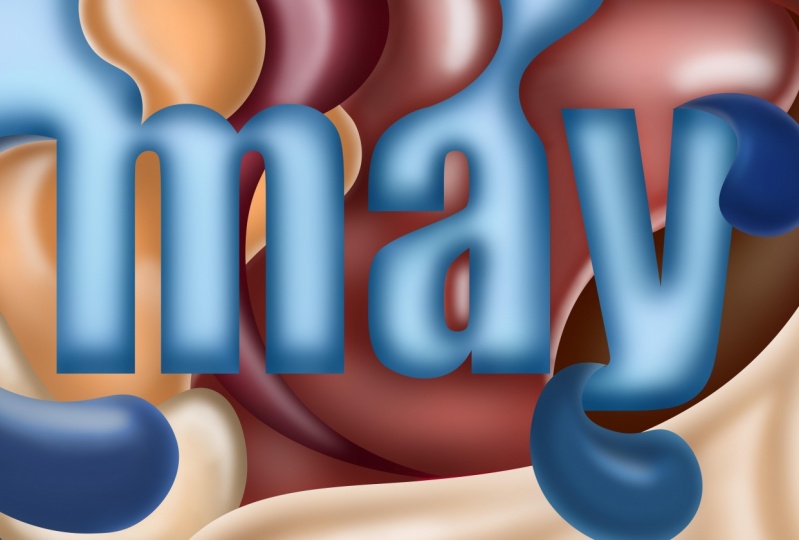
Tipografía creativa y arte abstracto del concepto de remolino
En este curso, enseñaré cómo puedes usar las formas básicas en Adobe Illustrator y Photoshop para crear hermosas obras de arte abstractas que pueden usarse para el diseño de embalajes, pósters o proyectos divertidos personales.
Te guiaré a través de todo el proceso de crear las formas en el ilustrador y importarlas en Photoshop STEP-BY-STEP. Mostraré cómo distorsionar las formas alrededor del texto con la herramienta de pen en el ilustrador, o crear todo directamente en Photoshop sin usar Illustrator. También te mostraré cómo usar máscaras de recorte y sombreado para que las formas planas aparezcan en 3D y tengan un efecto brillante para ellas.
1. Introducción: hola y bienvenidos a esta clase sobre la creación de arte abstracto tres D divertido en Adobe Illustrator y Photoshopped. Recuerdo cuando aprendí por primera vez a crear arte como este, y realmente trajo mi diseño gráfico a un nuevo nivel, y la gente estaba mucho más impresionada con este tipo de ilustraciones que crearía para diseño de carteles o producto diferente embalajes. En este curso, todos vayan contigo, paso a paso para esbozar tu obra de arte y traerla en ella será ilustradora y fototienda. Te mostraré cómo crear formas, usando la herramienta lápiz y otras herramientas e ilustrador para obtener los conceptos perfectos que quieres retratar. Entonces te mostraré cómo llevar tu obra de arte a la fototienda y luego, usando técnicas de pintura digital y cepillado, te mostraré cómo agregar profundidad y sombras y reflejos a tu trabajo para realmente traerle una profundidad de tres D a ella. Me encanta crear este tipo de arte, y puedes usarlo en concepto de packaging de producto son arte de póster divertido o una variedad de cosas diferentes. Me emociona ir junto con ustedes en esta clase y ver algunos de sus proyectos tan pesados y rollar botón y empecemos 2. Crear los bocetos de concepto: así que para empezar, me gusta esbozar una idea básica general de lo que voy a estar haciendo. Sólo que tengo un buen punto de partida cuando me meto en Adobe Illustrator y Photoshopped. Esto no es alguien que tenga que hacer. Y así podrías saltarte este video si quieres, pero esto va a ser una idea general de qué? Voy a empezar. Entonces voy a bosquejar Solo el general son nuestra zona de juntas, y voy a tener este aspecto como un diseño de empaques para, como, helado o leche o algo así. Entonces voy a tener, como, como, un gran movimiento en ello, Digamos que va a ser como un anuncio o algo así. Entonces eso es en, uh um y ha sido esto fuera un poco más. Y así tengo mi texto y voy a tratar de dibujar algunos grandes ya sabes, helado o remolino buscando formas alrededor de esto. Toma este diseño de fondo. Entonces vamos a tener la parte superior de la M. Es stand en esta zona. Y como dije, solo estoy tratando de tener una idea general de algunas formas diferentes para que esto se vea un poco más orgánico, y quiero integrar el texto en las formas. Por lo que parece más que forma parte de la ilustración y de esta cantidad aquí. Y no tengas miedo de agregar algunas formas realmente grandes. Alguna mente, incluso encubrir un poco el texto. Tan solo quería lucir realmente fluyendo y tener una buena sensación al respecto. Algunos invitados dan un poco esta siguiente parte para que veas lo que estoy haciendo ahora. Ya que querían tener más de una sensación lechosa y fluida, voy a añadir algún tipo de formas de gotitas grandes. T tener un poco más de diversión con un como este. - Entonces ahora que estoy hasta este punto, se puede ver que hay todas estas formas diferentes y todas parecen que están fluyendo juntas. Y todas estas grandes gotitas que puedes ver que tengo aquí hubiera hecho es que he pasado por algunos de los bordes, derecho tengo aquí NF acabo de dibujar y saliendo de esos bordes así como este, por ejemplo Puedes ver este borde lo hago por aquí y luego acabo de agregar que entrando así parece que fluye hacia las formas y Así que eso es algo que puedes tener en cuenta cuando estás dibujando algunos de tus diferentes remolinos o formas. aire que sale de él es que puedes tener esos fluyendo a diferentes rincones y hendidura para que se vea un poco más integrado en tu diseño. Y así no es perfecto. Pero al menos ahora tengo un buen punto de partida y conozco la dirección que quiero ir. Una vez que puse esto en Photoshopped, un ilustrador. Entonces ahora lo que voy a hacer es agarrar mi teléfono o puedes conseguir un escáner, y sólo voy a tomar una foto de esto de verdad rápidamente para referencia, y luego voy a tirarlo un ilustrador. Empezaremos en el siguiente video. 3. Añadir formas y conceptos en Illustrator: Por lo que hay dos formas de crear esta obra de arte. Ambos están consiguiendo este show fotográfico. Pero una manera es ilustradora, y la otra forma es simplemente quedarse en la tienda de fotos con todo y hay algunas ventajas para cada uno y las desventajas enseñan. Y así te voy a mostrar el en el sectorial en ambos sentidos para que puedas decidir qué va a funcionar mejor para tu proyecto. Entonces lo que voy a hacer es iniciar ilustrador para esto y agarrar el boceto que hice para el concepto. Entonces voy a copiar eso y luego volverlo a poner. Illustrator a usar es mi referencia. Entonces solo voy a escalarlo un poco y como ha terminado en el video de periodos, esto solo va a ser una idea áspera en Así que tú Lo que puedes hacer es usar la herramienta de bolígrafo o como quieras , y en realidad ir a través y mano, dibujar todo tu tipo, o puedes usar solo algún fondo. Y en realidad tengo un fondo que basé este tipo alrededor, um, um, digamos otra vez suave. Y así lo voy a escribir para que ya lo tenga aquí mismo. Y así centraré esto en nuestra pizarra donde me gusta, Eso se ve bien. Y luego tocaré turno, y luego control o mando. Ah, y eso va a crear estos contornos para que pueda trabajar más fácilmente con nosotros. Ahora, una de las otras cosas que va a ser importante es tener una buena paleta de colores. Y entonces lo que me gusta hacer es ir a, uh, color adobe. Entonces color adobe dot com. Y, uh, tienen realmente buen recolector de color. Este es un parecido al de ilustrador para esto solo voy a ir a explorar y solo voy a encontrar un esquema de color que ya me gusta. Y así, para mi tema, estoy pensando que voy a ir por una especie de look de chocolate. Y así vamos a ver qué surge cuando tipeo en chocolate. Y así estos aires unos colores de aspecto divertido, me gusta tener un poco de azul ahí dentro. Entonces solo voy a guardar esto, y luego va a ir directo a mi biblioteca. Y así voy a crear nueva biblioteca. Llámalo nuevo. Entonces una vez que tengamos todo esto ahora voy a ahorrar, y ahí está Así que voy a volver a Adobe Illustrator y quiero sacar mi panel de biblioteca, así que ve a ventana y luego bibliotecas y ahí va a sacar todas mis bibliotecas, así que iré a biblioteca y aquí está mi biblioteca mu. Y vi personas que han tenido problemas con nosotros en el pasado que no se hunde con sus bibliotecas. Y así solo quieres asegurarte de que tus bibliotecas estén actualizadas. Es posible que tenga Teoh haga clic en uno de estos iconos y asegúrese de que tiene la actualización puesta a hundirse, y luego aquí está su paleta de colores. Y así voy a, derecha, Haga clic en eso y diga, agregue dos muestras. Y ahora aquí tengo todos estos colores añadidos a mi panel de muestras. Y así para esto, quiero que el texto principal del estado de ánimo sea una especie de blanco, y así lo voy a agregar a ese color, y puede ser un poco difícil de ver, Así que por eso solo lo hará azul por ahora. Y luego voy a empezar a dibujar algunas de las formas del concepto Sketch lo hizo. Y así aquí mismo, voy a añadir esta M estirándose en todas estas diferentes formas estaban aquí tan hippie para mi herramienta de bolígrafo, y voy a hacer clic arriba en la parte superior de ellos. Y quieres asegurarte de que el punto de anclaje esté chasqueando aquí mismo. Y así me voy a asegurar que eso encaje al punto de anclaje y uso ah, control o espacio de comando. Yo los sostengo abajo para el matorral, tú zoom e ilustrado porque lo hace un poco más fácil. Y pincharé aquí arriba y luego mantendré pulsada opción o Alter y puedo mover punto de anclaje alrededor y cambiar para limitarlo. Y luego pincharé por aquí abajo, ya sabes el fondo y luego lo traeré por ahí. Y si se pone difícil de ver porque el ilustrador rellena la forma automáticamente golpeará Mayús X, y luego simplemente lo cambiará a delinear en eso y oh, haz clic arriba por aquí y el hombre de nuevo a la M. Asegúrate de que broches de presión y conectados ahí mismo. Eso me gusta ahí mismo. Entonces voy a golpear opción o todo para conducir el punto de hundimiento otra vez y luego cerrar el camino y luego volveré a golpear el turno X para llenar esa forma de nuevo dentro. Y ahora aquí mismo, no conecta todo el camino. Suela. Usa mi herramienta de selección de drogas golpeando un y luego daré clic en este camino aquí mismo. Y solo arrastraré eso hacia abajo y luego pincharé en este punto de anclaje y lo arrastraré un poco más para que quede un poco más fluida de eso. Y ahora, para asegurarme de que esto no es demasiado torpe aquí mismo, agarraré ese punto de anclaje y solo arrastraré esto un poco hacia arriba. Y en realidad me gusta eso porque agrega un poco más de piso ahí mismo. Y tengo esta gota aquí mismo que voy a dibujar, así que haré lo mismo. El P para el lápiz. Empezaré aquí mismo y me voy a arrastrar y no me importa superponer formas. Entonces aquí y allá en un barco X. Asegúrate de que pueda ver lo que estoy haciendo y arrastra por aquí. Y luego cuando quiera cerrar el camino para asegurarme de que se quede de esta forma todo hit opción o todo primero y luego voy a hacer clic y mantener presionado y luego puedo arrastrar el punto de anclaje por donde quiera. Y así lo voy a cerrar ahí mismo. Y luego utilizo una herramienta de selección directa y solo ajusto un poco las cosas. Asegúrate de que sea agradable y suave, y eso se ve bastante bien. Y luego, uh, golpeó turno X otra vez. Y solo voy a hacer de esto un color diferente para que puedas verlo. Y voy a sólo unas cuantas cosas este año en un poco más. Entonces eso se ve realmente bien. Y voy a pasar por esto y hacer lo mismo con algunas de estas otras formas. Ve a Theo, conduce alrededor, opción, luego haz clic y arrastra. Y luego, ya sabes, conecta eso aquí mismo para asegurarte de que parezca que es parte de la O. Y él es mi herramienta de selección directa y ajustar la mitad sólo un poquito. Y ahora se puede ver aquí mismo. Algunas de estas ha quizá no estén totalmente conectadas, y así que solo quiero pasar y asegurarme de que esos aire todo se rompió a las formas. Porque cuando exporto esto, traiga una tienda de fotos. No queremos ningún problema con las formas que no se conecten. Y una cosa que va a ayudar con muchos de ustedes probablemente sea llenar primero el fondo , porque esa podría ser una de las cosas más difíciles de averiguar una vez que haya llegado a cierto punto. Y así lo que puedes hacer es solo que tu herramienta de lápiz y luego simplemente haz clic y luego solo rellena algunas formas de fondo grandes, y eso es un poco demasiado lejos. Entonces voy a No vas a bajar un poquito. Ponla aquí y ahora quiero algo Eso es tabaco hit shift command y soporte izquierdo o control de turno y Soporte izquierdo. Y luego voy a cambiar el color y puedes ver que está en el fondo. Y así voy a llenar unas cuantas de estas formas en el fondo sólo para que todo esté cubierto y no tenga que preocuparme por ello tanto más tarde y equipo aquí y ella está mando dejó corchetes y de vuelta a la espalda, y yo te tire hacia arriba en mi panel de color y puedes tener esto expandir y colapsar. Pero hasta que veas estos controles y me gusta usar el modo de brillo de saturación de matiz para que pueda cambiar, las cosas serán más fáciles. Eso es lo que prefiero. Y así ahora nos estamos llenando mucho más. Y voy a golpear la M para mi herramienta de forma y simplemente arrastrar una caja justo aquí para poder llenar el resto de esto con bastante facilidad. Y entonces los hombres deberían dejar corchetes y eso a la espalda, y voy a usar otro tono de marrón. A lo mejor un poco más de saturación ahí dentro. Y ahora que tengo todo el asunto, Phil, entonces realmente puedo hacer el movimiento y algunas cosas otras formas blancas como, originalmente quería. Y puedes empezar a cantar como se va a ver. Y así ahora esto realmente está empezando a tomar alguna forma. Voy a añadir algunos remolinos más aquí mismo. Bueno, gotita de leche saliendo de su retención en opción para sacar ese punto de anclaje, utilizo mi herramienta de selección directa. Digamos que esto está cubriendo eso un poco demasiado algunos y arrástrelo por aquí anime y entrar, acercar un poco más y asegurarnos de que eso parece que se está conectando derecho a eso . Ah, porque lo que vamos a hacer es agregar algunas sombras más tarde, así que parece que está frente a la y está saliendo de ella. Entonces conduces eso y un poco más ahí mismo. Vamos a hacer esto un poco diferentes tonos de color sólo para que pueda ver dónde está . Y no estoy demasiado preocupado por ello porque voy a meterme con todos estos colores después de todos modos . Y así ahora tengo esta gran forma saliendo de aquí que quiero tapar algo de eso Oh , con Teoh. Añade algún tipo de efecto drama divertido tan bien, más rápido fuera de aquí y arrastra eso hacia abajo y hazlo subir justo ahí. Opción, conducir el punto de anclaje por aquí. Genial ahí y luego agrega una línea grande justo aquí. Y no estoy demasiado preocupado por ser súper preciso porque, como dije, sólo voy a seguir, mover las cosas de todos modos. Buen sinker jugando y todo eso. Y así que esa es una gran corriente de leche que viene ahí mismo. Y una cosa que vas a querer mirar es un contraste, porque si tengo demasiado de este blanco, entonces va a ser más difícil ver ese texto. Y así tengo un poco de azul en mi paleta de colores, así que tal vez quiero hacer esta forma azul, y luego puedo agregar algunos. Por qué las formas que salen de eso aquí mismo. Ahora que tengo esta porquería hecha, voy a ajustar un poco y que cuando pueda hacer blanco, porque no va a ser tanto que va a dominar el texto en el medio. Y así ahora el resto de esto, voy a hablar un poco más rápido. Vamos a añadir un poco alrededor del cabello y otro truco que me gusta usar si estoy creando algunas formas al igual que esta forma que tengo aquí y lo quiero detrás de ciertas formas. Pero frente a otros para controlar que solo puedo golpear control o comando X, Y entonces puedo buscar las formas que la quiero delante y detrás. Entonces, por ejemplo, puedo ver todas estas formas aquí mismo están frente a ese gran bloque marrón, y quiero que esa forma que acabo de hacer para estar entre esas y los soldados golpearon ese bloque marrón . Y luego si vas dedo del pie editar, puedes haber dado un paso al frente. Y ahora va a ritmo esa forma frente al bloque que había seleccionado, pero detrás de todo lo demás que está delante de ese bloque y cambiaré ese Teoh diferente color azul y ajustaré un poco la forma. Y ahora algunas de estas otras formas de aquí voy a entrar, y eso termina ahí mismo y lo mismo, Control X y yo queremos que estemos frente a todas estas formas de Brennan, y así esto está frente a eso. Y así le pegaron al control F, y ahora está detrás de ese azul. Pero ahora, como parece que quiere pasar todo el camino por esto, sólo voy a extenderlo por aquí con otra nave. Entonces esa es una de las ventajas de iniciar esto es un ilustrador. Es realmente fácil trabajar con, y tengo muchas herramientas que pueden controlar lo que estoy haciendo. Entonces oye, controla X y luego quiero que al mismo nivel es esto? Entonces voy a dar clic en esto y luego golpear el control F, y ahora se trata justo ahí, aunque tengo esta otra forma marrón que está delante de eso porque se puede ver donde está apareciendo ahí mismo. Entonces solo voy a agarrar esa forma y golpear el control y luego me fui Bracket, y tiene que mandar eso de vuelta. Sólo un objeto. Y así me estoy acercando realmente. Ahora puedo ver esto. Ahí está esta gran mancha que se está poniendo, ah como en el camino con algunas de estas tangentes. Entonces voy a cambiar el color en estos solo un poco y hacer un poco más brillante, y voy a golpear mi total de rotación son para la herramienta de rotación, y voy a dar clic en la base de eso Y sólo voy a girar un poco justo así eso no está causando tangentes divertidas en estas áreas, y sigue haciéndolo sólo un poquito. Entonces lo voy a mover allá arriba ahora se ve un poco mejor, y quiero unas gotas aquí mismo. Y así solo voy a golpear el control C y luego cambiar el control o comando V, y voy a dar clic en eso y Hit pidió mi herramienta de escala click en la parte inferior de aquí y sólo voy a bajar eso un poco. Y no voy a sostener turno porque no me importa tanto ser proporcional porque quiero lucir un poco diferente a eso. Y así me gusta eso y hago vamos a hacer este chocolate y así sucesivamente. Y creo que esto se está acercando realmente. Sólo voy a tener una forma más aquí arriba detrás de ahí. ¿ Es ese un color diferente del azul? Y aunque es bueno y voy a golpear el control X y solo quiero colocarlo justo detrás de eso , lo vemos para hacer eso, puedo tener objeto y luego o editar y luego pegar en la espalda. Y eso sólo va a pagar Siéntate detrás del objeto que tengo. Um, un problema aquí mismo es que tengo esa forma al frente y así no hay nada que necesito detrás de esto están frente a esto. Y así sólo voy a tener control de turno, soporte derecho, y eso lo va a mandar al frente. Ahora da click en esto y quiero que esto solo sea un tono diferente de azul ahí mismo. Entonces haz clic ahí y voy a ir a mi barra de saturación de matiz. Y luego estaba desnatando sin un poquito y hagámoslo un poco más oscuro, y quiero que esto tenga una transición mucho más fluida con esta otra forma. Algo es mi herramienta de selección directa. Y sólo voy a arrastrar esto a la derecha para que esté conectado con ese, y luego voy a tirar hacia arriba. Y así ahora tengo esta pequeña tangente en el camino ahí mismo, así que sólo voy a subirla un poquito. Entonces no está causando ningún problema por ahí. Y así creo que esto se ve bien. Y ahora te enseñaré cómo prepararlo. Teoh, trae a Photoshopped. 4. Preparación de obras de arte para Photoshop: Voy a eliminar esta referencia ahí tengo, y voy a agarrar todas estas capas y asegurarme de que puedas ver qué está pasando. Voy a dar click en mi posterior en mi panel de capas y voy a ir a este pequeño menú para el panel y voy a dar click en liberar dos capas como secuencia. Y ahora lo que va a hacer es separar todas estas capas en su propia capa individual. Y así voy a dar clic en todos estos y todos arrastrar aquellos fuera de esa capa principal y luego voy a clic en esa capa original uno. Voy a golpear delete porque no hay nada en él y sólo voy a asegurarme de que haya algo en todas estas capas y todo se vea bien. Bajaré a archivar y luego a exportar como, y voy a ir al archivo que quiero, y lo voy a guardar como tienda más. Nuevo. Son mundos. Ah, quiero asegurarme de que estoy usando los nuestros tableros porque eso lo va a recortar a la zona que tengo en mi están aburridos. Tengo este cultivo, así que tengo alguna forma saliendo. Pero si sí tienes formas saliendo. Vas a querer asegurarte de tener tablero de arte seleccionado cultivo de cereal cualquier imagen extra fuera , y luego tendré exportación. Y quiero asegurarme de que sea un RGB y tendrá, Ah, alta resolución. Quieres tenerlo configurado para escribir capas y estás máximo sin marcar en una habilidad de edición y luego golpear. Está bien. Y ahora en el siguiente video, te mostraré cómo abrirla y Photoshopped. 5. Importación en Photoshop: De acuerdo, así que ahora ya estás listo para abrir ese archivo Y Photoshopped, Vamos a abrir la cabeza y dar click en la primera falta de disparo que creamos y que había abierto. Y ahora tenemos la misma obra que exportamos de Adobe Illustrator. Si lo hiciste bien, deberías tener todas estas capas separadas y el panel de capas como sus propias capas individuales . Y la canción de grupo de esta tiene el comando de turno G y en grupo eso y de hecho, esa es mi capa de texto principal. Entonces sólo voy a nombrar eso sin texto. Y ahora lo que me gusta tener es mi auto select and show transform controla un cheque para que pueda seleccionar fácilmente diferentes capas. Y puedo ver los controles de transformación en esos. Y me gusta que después seleccione porque eso significa que va a seleccionar cada capa individualmente. Y así ahora que estoy en este punto, quiero seleccionar este texto de ánimo y estas otras dos capas y veamos dónde están en su en diferentes áreas. Y así voy a arrastrar esta capa que está clara en la parte superior, y la voy a arrastrar hacia abajo a esas otras capas, así que la voy a arrastrar hasta y la voy a arrastrar hacia abajo a esas otras capas, aquí, pero ahora puedes ver y moverte hacia arriba debajo de esa otra capa azul. Y así lo que puedo hacer es hacer clic en esta capa y golpear control o comando, y luego todos seleccionar esa capa, esta transparencia trans Lexa de esa capa. Y luego voy a dar click en esta forma azul que quiero lucir como está detrás de eso y luego encontraré donde está la forma azul, y luego solo voy a dar clic en esta herramienta de máscara pega toda nuestra opción, y luego voy a dar click en eso. Y eso va a eliminar todo lo que he seleccionado de eso más adelante. Pero lo bonito de esto es que si sostengo turno y hago clic en la máscara, sigue ahí. Por lo que todavía puedo usar eso si necesito. Y ahora que todas estas capas se están tocando aquí mismo, puedo golpear el control o el comando E, y eso las va a fusionar todas juntas porque quiero que estas todas estén conectadas para que cuando la esté cepillando, sea va a ser mucho más fácil, y eso se ve bien para todo lo demás. Una cosa que quiero asegurarme de que también hago es ir a mi imagen y luego cambiar el modo a 16 bit. Y eso lo va a hacer para que mientras te estás cepillando en algunos de los diferentes sombreados y colores en esto, um, no va a haber bandas. En ocasiones notarás si estás metido un poco cuando estás usando la herramienta de pincel o pintando. Verás esto, uh, uh, genial y banding que va a causar líneas y distorsiones en tu obra de arte. Por lo que tenerlo en 16 bit es bueno para mientras estás trabajando en él y luego puedes cambiarlo nuevo a un poco más tarde. Y así nos vemos bien aquí mismo. Sólo recuerdo que me quedan estas dos formas que me refiero a moverme un poquito por esos tendones ahí mismo sobre el él. Y luego golpearé Control E y me aseguraré de que esos aire se fusionaron juntos. Y eso es todo lo que necesitas para que esto se prepare para empezar a pintar. Y así en el siguiente video, te voy a mostrar cómo empezar a sumar algunas de las diferentes sombras y reflejos para realmente hacer de este nuestro trabajo de un destaque 6. Añadir sombreado y profundidad a la ilustración: De acuerdo, así que ahora por la parte divertida, voy a Teoh, encuentra algunas formas que quiero empezar a agregar. Ah, algo de profundidad al primero. A mí me gusta empezar con un fondo y trabajar mi camino arriba, así que voy a empezar el fondo. Añadiré una nueva capa justo aquí encima de ella y luego mantenga la opción o todo, y luego haga clic para que se vaya a crear una máscara de recorte en la parte superior de esa forma inferior. Y entonces tendré esta forma aquí mismo, y haré clic en el modo de mezcla y pasaré de lo normal a multiplicarse. Y esto solo organiza mis capas para que pueda tener mucho más control sobre lo que está pasando . Y así ahora tendré carne de res con herramienta de pincel aquí y todo bien, click y luego escalarla y asegurarme de que la dureza sea un cero. Y lo que también me gusta hacer en Ah, oye, mira, puedes tener opción y luego hacer click derecho y arrastrar de ida y vuelta y de lado va a cambiar el tamaño y arriba y abajo. Esto puede cambiar la dureza, y se puede ver aquí mismo hay un pequeño adelanto rojo de cómo se va a ver si tuviera cero, eso va a cambiar mi capacidad. Uno es 10 cinco o seis. A 60% 0 va a ser 100%. Y ahora puedes ver ese adelanto un poco mejor. Y en nuestro Mac, el atajo es control, opción e izquierda, haga clic y arrastre de ida y vuelta. Entonces ahora que tengo mi color seleccionado, estoy en un color oscuro y voy a empezar en, como, 30%. Y voy a empezar a cepillarme donde quiero algunas sombras, y eso se ve un poco demasiado oscuro ahora mismo. Así que voy a golpear controles, oído Comando Z, y voy a bajar al 10% y, uh, acercar un poco y luego sólo añadir eso aquí un poco, justo donde parece que hay una sombra detrás de eso forma, y voy a añadir un poco detrás de Mary, y voy a añadir algunos por aquí y empezar a añadir sombras sólo un poco donde va a traer un poco de muerte, y eso está un poco demasiado oscuro ahora. Y puedo hacer esto un poco más grande y de repente poner en algún chef está justo ahí. Y así eso es lo que puede conseguir para los hombres en. Y ahora voy a añadir otra capa encima de eso y luego tenía opciones son todas y luego hacer clic en crear, no equipar máscara y luego cambiar ese modo de mezcla a la pantalla enter. Y ahora volveré a usar mi herramienta de pincel. Y luego le pegaré a X para asegurarme de que esté sobre blanco. Y luego entraré y añadiré algunos reflejos blancos, y eso se ve un poco demasiado justo ahí. Y así le pegaré a Control Z. Y luego mandaré mi pasividad abajo para decir como, tres personas. Y eso ya se ve un poco mejor aquí. Y agreguemos algunos aspectos destacados por aquí. Entonces estamos ahí dentro y tiene unos bordes más afilados, y ahora eso ya está sin duda se ve bastante bien aquí mismo. Y lo que puedo hacer para suavizar todo es que puedo seleccionar mi capa aquí mismo, que un filtro y luego desenfocar, y luego simplemente Goshen desenfocar. Y luego si desenfoco eso, lo va a suavizar aún más. Y en este momento solo estoy tratando de bajar algunos colores base como punto de partida para agregar algo de profundidad a esto, así que voy a dar clic en las sombras. Y luego, en lugar de ir a Teoh Goshen, difumina cada vez. Solo puedo usar mi filtro más reciente con un atajo corto. A te da justo aquí, así que eso es control a la izquierda. Entonces voy a golpear el control F, y automáticamente va a desenfocar esa capa. Y así ahora que estoy listo para empezar en mi siguiente capa, solo haré clic en esa capa. Y lo que he hecho es crear una acción, así que no tengo a Teoh seguir creando nuevas capas y enmascarándolas a esa capa inferior. Puedo entrar en mi panel de acciones, y si vas a la descripción del curso, tengo un enlace a esta acción donde puedes descargarlo. Y si quieres carga de dedo, la acción y yo tengo que ir a es el menú arriba en el panel y tenía acciones de carga y luego seleccionar el archivo. Y una vez que estés listo, solo tienes que hacer clic en la capa que quieras y luego hacer clic en la acción en ella jugar, y luego crea automáticamente estas dos capas y como el modo de mezcla correcto. Y así ahora solo puedo hacer clic en la capa inferior y usar mi herramienta de pincel y asegurarme de que esté en negro y empezar a cepillarme en algunas sombras. Voy a hacer este 10%. Iba a cepillarlos y un poco mejor. Y como algo de sombra aquí abajo, un poco más de escritor ahí dentro. Ahora todo lo que estoy haciendo es hacer la ilusión de que hay profundidad con estas capas. Y así tengo esta capas marrones de mi capa inferior. Esta está ligeramente por encima de eso, y así estas capas se airean encima de eso. Una vez solo estoy agregando algunas sombras más y reflejos Teoh, donde estas capas o creando sombras en estas y se ve bien. Voy a golpear control o comando f explorar eso un poco. Y este tu desenfoque más reciente no fue suficiente. Entonces solo puedo volver a entrar y desenfocarlo a algo que quiero escoger manualmente, y eso fue un poco mejor ahí mismo. Y ahora entraré en la capa de resaltado y añadiré algunos reflejos. Ve al 3% si hay esa experiencia de una milla aquí y hagamos esto un poco más brillante. Entonces tengo un punto culminante decente ahí mismo, y queremos un buen resaltado y hagamos que parezca que este chocolate de aquí está viniendo fuera de eso está viniendo a través de eso. Ah, así que para hacer eso, solo le agregas un poco de reflexión encima. Y ahora solo difuminemos esta capa aquí mismo. Ahora suaviza un poco esos reflejos. Y ahora esos se ven realmente bien ahí y en realidad se pusieron un poco más detallado puedo entrar aquí y luego sólo voy a añadir otra capa nueva, opción tirar hacia abajo o todo. Asegúrate de que recorté eso hasta ahí. Y luego voy a usar mi lápiz herramienta hit p con lápiz aquí. Y ahora puedo empezar a ser un poco más precisa sobre dónde quiero añadir algunas de estas reflexiones. Entonces voy a dar clic aquí, y luego voy a añadir una reflexión justo alrededor de esta zona. Y luego este trabajo similar al ilustrador puedo mantener presionada toda la opción y luego arrastró el punto de hundimiento alrededor y luego dr por aquí así, y luego mantener presionadas todas sus opciones primero. Y luego puedo ajustarme donde quieras ese último punto pensador, y eso se ve bastante bien. Y así da click en esa capa que quiero usar como línea de reflexión justo ahí y luego todo hit control o comando. Y luego golpearé la máscara de recorte y eso va a crear una máscara para la capa vectorial desde ese camino hacia esta capa. Y eso es realmente bonito, porque entonces puedo controlar la máscara más tarde. Y este es un uso técnico, uh, para crear este arduo trabajo desde cero si no quería usar ilustrado. Y así tengo eso ahí mismo. Voy a dar clic en la capa y luego golpear mi herramienta de pecho y luego asegurarme de que estoy en blanco y luego todo de solo cepillarnos un poco de reflexión ahí mismo. Y tal vez eso es un poco demasiado, uh, arrastrar la capacidad. Y luego, si tengo esto seleccionado, si tengo mi panel de propiedades arriba, puedes ir a ventana y propiedades. Eso te va a dejar mientras esto esté seleccionado, cambiar el emplumado y los algunos de los ajustes de la máscara, y así si quiero una pluma que enmascarar un poco, entonces empieza a un poco más de profundidad. Y así lo voy a hacer un par de veces más con la misma capa en zonas, creo que habría un reflejo. Entonces esto me estoy imaginando un reflejo de la O donde esa línea recorre ahí mismo. Y así va a ser este pequeño reflejo falso ahí mismo. Y podría hacerlo de nuevo aquí mismo en otra capa. Y solo puedes seguir haciendo esto tanto como quieras. No quieres ir por la borda. Pero lo que encontré es tener una buena cantidad de detalle hace que se vea realmente realista. Y una forma en que puedes hacer eso un poco más fácil es agregar múltiples máscaras al mismo tiempo. ¿ Múltiples formas con una herramienta de bolígrafo? Entonces voy a golpear mi herramienta de bolígrafo, y voy a agregar algunos justo aquí en una opción de arrastrar eso aquí abajo y llamar a una buena ahí. Y como está detrás de estos, no me voy a preocupar por ser preciso ahí mismo y aguanta opción antes de dar clic en ese último movimiento de stop justo por aquí. Y como dije, puedo agregar múltiples formas a la vez para la misma capa, así que no tengo que hacerlo. Demasiadas veces. Así que ahora asegúrate de que esto es como combinar formas y voy a dar clic aquí y añadir otra justo ahí. Y esto es de nuevo donde apenas un poco de destaque especulativo? Lo voy a agregar ahí, y puedo algunos otros aspectos destacados por aquí y hacer clic fuera de eso. Y tengo estas tres formas que se ven todas como de la misma forma. Por lo que entro aquí a esta máscara, voy a golpear control y enmascarar. Y ahora estas Todas estas formas estaban aquí están todas en esa máscara. Y así voy a dar clic en la capa, mi herramienta de pincel y empezar a cepillar en No, eso es demasiado. Entonces voy a ir 4% aquí mismo. Capacidad sobre ruso, Sólo un poquito justo ahí. Y nadie tiene reflexión de Cem ahí mismo. Y esto se acerca justo por aquí. Entonces digamos que quiero un poco más brillante por ahí y un poco menos por ahí. Y así ahora se puede ver cómo esto comienza a traer mucha más profundidad a esta ilustración a partir de algunas de unas líneas agudas. Y así hago clic en la máscara aquí mismo, y sólo voy a plumas a los mayores y puede que me vaya un poco más emplumado en esos, así que no son del todo tan duros de líneas. Y ahora esto es que está empezando a lucir realmente chocolatey y realmente conseguir. Y ahora una de las últimas cosas que me gusta hacer es agregar algunos reflejos realmente brillantes justo alrededor de algunos solo para hacer estallar un poco más. Entonces voy a volver a bajar a mi capa de resaltado la alta original últimamente, y luego volveré a tener herramienta de pincel. Y luego todo dijo esto como 20%. Y entonces sólo voy a tener algunos reflejos realmente brillantes justo en estos bordes, y lo va a diferenciar de todo lo demás realmente bien y sobre todo justo aquí. Sí, estoy cepillado eso. Y así ahora se puede ver esto un gran trozo de chocolate donde si tomo todas estas capas y las escondo, pero estoy revisando el ícono pequeño ojo, Entonces se puede ver cuánta de una diferencia hicieron todas esas diferentes capas. Y así todo empezó a ir un poco más rápido con estas siguientes capas, voy a hacer clic en esa siguiente capa, a mi acción, añadir sombras y reflejos, e ir a mi capa de sombras y empezar a cepillarme en algunas sombras. Y aunque alguien aquí y digamos que solo quiero crear un pequeño león sombra, medio al azar justo ahí y eso es una madre sombras justo aquí. Iré a Filter. Simplemente desdibujaré esa capa. Y podría hacer eso una vez más e incluso lo dice un poco. Iré a mi punto culminante, capa la herramienta de pincel y luego empezaré a agregar algunos reflejos. Asegúrate de que esté en 4% y esto será un verdadero gran punto culminante aquí y cuanto más nítido queremos el filo. Simplemente puedo hacer mi pincel un poco más pequeño y mostrar que ahí mismo y luego donde eso y eso se ve bastante bien. Y de hecho, lo soy apostador una vez más. Y ahora, en algunas reflexiones sobre esto, agrega una capa. Deja que eso a las capas anteriores es mi herramienta de lápiz y empieza a agregar algunos reflejos, y una cosa que puedes hacer mientras estás jugando con estos pases, mantén pulsado el control, y luego mientras los estás creando, puedes mover las cosas. Si te metes tan rápido que y vuelves aquí y arma controla y enmascara eso y luego cepilla en el punto culminante justo aquí. Y creo que eso se ve bastante bien por ahora. Entonces voy a dar clic en mi siguiente forma aquí mismo, ir a mis acciones, jugar la acción y empezar a agregar algunas sombras y reflejos fueron rápidamente. Iré a un costado y ruso, algunas sombras. Estamos aquí, y como esto es un poco más arriba, se pueden ver todas mis diferentes capas. Esta es una de las capas más cercanas a la parte superior, y así no estoy agregando mis sombras más en la parte superior de ella que en los lados porque, como puedes ver con esta capa en el lado chocolate en la parte inferior, hay esos reflejos a un lado, y eso hace que parezca que está más al frente. Y entonces eso es lo que voy a hacer con esta forma azul aquí mismo también, y por hacer un proyecto como este, una cosa que va a ayudar es tener una tableta como si tienes un paseo en tablet, donde no son pro, puedes usarla como tableta estilista para controlar la computadora, y eso lo va a hacer mucho más fácil, agregando algunas de estas diferentes formas. Entonces agrega un par de sombras más aquí mismo. Y uno simplemente estaba bien. Ah, claro, azul esa capa Y mis reflejos. Um, tenías algunos reflejos realmente brillantes justo aquí arriba. Voy a añadir un poco de luz de fondo aquí mismo a los lados de esto, y luego voy a desenfocar esa capa. Pero no te preocupes, solo Y esos, vamos Y entonces iré a los lados y le agregaré los reflejos realmente valientes. Y luego iré por aquí, asegúrate de que te pongas eso bonito y genial. Ahora no quieres ir demasiado por la borda en estos aspectos destacados. Se quiere justo lo suficiente para que le tenga un poco de dimensión, y así se puede ver que se ve bien. Pero necesito que Teoh desdibuje más algunas de estas otras formas. Algo que ir desenfocar ahora se ve un poco mejor en esos otros aspectos destacados. Lo mismo con la siguiente forma. Basta con dar click en él. Y en algunas sombras aquí, vamos a hacer eso un poco más oscuro por ahí. Y cuanto más sombreado pongas en estos, mejor. Se va a ver porque va a ser menos plana, y va a tener un poco más de dimensión. Así que empieza a añadir algunos aspectos destacados. Ahora esto y un bonito por aquí y no aburre estas capas. Y no quiero hacer eso demasiado. Vamos a la capa superior y sobre eso, y sólo estoy desbaste en estas formas ahora mismo. Teoh, hazte una idea de dónde estoy realmente rápido con la profundidad en todo este proyecto. Y así antes de añadir el es un más destacado detallado, sólo voy a tratar de obtener una sensación general de una profundidad de este proyecto. Entonces ahora estoy en el texto y asegurarme de que eso sea negro. Bueno, y esto, ya sabes, pelo esto voy a querer acercar un poco más algunas de estas sombras alrededor de los bordes. Ahora bien, si no tienes texto en tu proyecto, no vas a tener que preocuparte por esto. Pero si te dio tu solo quiero asegurarme de que entres y construyes un más detallado sobre los bordes. Eso que va a tener esa buena sensación. Y esto tiene ese disparo por ahí donde hay una gran gotita en Eire y su sombra por aquí, también. Y ahora, con algunas de estas formas más ligeras. Se puede ver que las sombras empiezan a ponerse un poco fangosas porque son negras. Pero una sombra real en un color como este no sería negro. Sería más de un color marrón más oscuro. Y así lo que puedo hacer es ahora mismo, Um, puedo hacer clic en esa capa y entrar en imagen y luego ajustes y luego cambiar el tono y la saturación en ella. Y luego, si hubiera colorido, entonces puedo cambiar el color de Simoes Áreas oscuras. Aiken. Saca el poco de ligereza y luego cambia eso a más de un color marrón. Y así que eso es que se ve bastante bien ahí mismo. Y eso realmente trae mucho más realismo cuando los colores son correctos y eso es lo mismo con estas capas azules. Puedo entrar a esa capa de sombras y luego ir bajo ajustes de imagen, él y la saturación. Y entonces solo colorearé los ojos eso y lo haré más de un color azul. Y así eso va a mejorar realmente algo del look de las formas. Y así ahora volveré a entrar en esta capa e iré a mi punto culminante más tarde y pegaré la herramienta de mama , y quiero algunos reflejos. Y como esta ya es una capa bastante ligera, voy a cambiar mi capacidad del 20% sobre el blanco aquí mismo estoy jugando y eso va a sacar un poquito más de los aspectos más destacados en Eso es un poco más rápido y luego voy desenfocar esa capa. Hanno, difumina el Schuttler y sólo tenemos unas cuantas capas más que necesitamos. Tengo esta gotita azul justo aquí una gran cantidad de las capas de profundidad y luego agrego algunas sombras aquí. Y cuando estés debajo de las sombras, solo piensa en dónde estarían las sombras. Entonces me estoy imaginando alguna luz falsa justo en medio de aquí. Y así voy a tratar de mantener las sombras al aire libre. Entonces aquí mismo hay una sombra de ese lado y resalte. Y ni siquiera tienes que ser muy preciso con esto porque como lo estás difuminando , va a arreglar muchos de esos problemas. Haga clic en la capa de sombras, pero un filtro y donde La sombra Y ahora, aquí mismo, voy a volver a la capa de resaltado y volveré a añadir algunos de los reflejos agudos en ésta otra vez, me gusta no envió las otras formas. Voy a tratar de mantenerlo de este lado porque de ahí viene la mayor parte de eso. Ese resalte aquí mismo. Y eso se ve bastante bien para esa gotita Ahora, aquí mismo, tengo estas dos gotas y están causando un pequeño problema porque el color en esto está haciendo que eso parezca casi una G de muy atrás. Y así solo voy a dar click en esa capa y luego voy a ir a mi imagen. Ajustes, matiz, saturación. Y podría simplemente cambiar el color de esa capa con bastante facilidad así y una forma alternativa que realmente me gusta más que eso. Si estoy cambiando el color para una capa entera como esa es simplemente bajar aquí a este ícono enfermo y luego hacer clic en un color sólido y luego simplemente elegir el color que quieras y luego ir a esa capa, mantenga la opción más antigua y luego enmascararlo a la capa debajo. Y ahora puedo hacer doble click fácilmente en ese color y escoger el color que quieras. Y así sólo voy a añadir otro tono de marrón para que parezca otra capa de chocolate como una gota de chocolate justo aquí y esa capa. Sus actos igual que cualquier capa debajo que esté recortada a la capa de forma principal. Entonces si solo hago clic en esa capa, puedo volver a subir a la acción y luego jugar eso. Y ahora va a crear dos capas encima de eso que todas todavía recortadas a la capa de forma principal , y estas puedo entrar y empezar a añadir sombras y reflejos de nuevo. Entonces aquí mismo, voy a añadir algo de sombra ahí mismo, un poco más de sombra justo en la parte superior. Y ya sabes dónde eso dónde y vas a resaltar capa y añadir algunos reflejos. Déjame ir al 3% de capacidad. Y en esto solo voy a agregar un poco de destaque todo el camino alrededor de la forma, mayormente en la parte superior. Y luego me refiero a azul esa capa. Y ahora volveré a entrar y sumaré mis reflejos más duros. Pero quiero mantenerlo en el interior de eso para que consigas un 20% de capacidad en lugar de despotricar, y yo haré lo mismo con esta capa más pequeña aquí mismo. Me gusta ese color marrón, así que voy a la configuración tener las sombras o reflejos otra vez y empiezo a cepillarlos. Pero aquí está la sombra en la parte inferior y mirando muy bien donde X zoom un poco justo aquí y 0333% de capacidad y descansando un poco de resaltado aquí arriba y luego ir filtrar desenfoque de lo que somos todo. Lo mismo es capa debajo, asegúrate de dónde esa sombra y luego ve a mi herramienta de mama de la capa de resaltado de nuevo y tenerlos esos reflejos más duros. Y ahora estoy en mis dos últimas capas, esta capa debajo oh, va a escuchar tenía el cobertizo en capa de resaltado. Encima de ella, haga clic en un aire de sombra. Y ahora que ya sabes agregar las capas de sombra y resaltar toda la velocidad a través este verdadero rapido y empezar a explicar el resto de la misma. Y ahora digamos que querías cambiar algunos de los colores de algunas de estas capas. Uno de los problemas es hacerlo usando ilustrador. Una de las desventajas de eso es que es un poco más difícil cambiar los colores de estos. Todavía puedes hacerlo como recuerdas. Yo cambio el color de eso, y puedo entrar en algunas de estas otras capas así. Esta gotita de aquí y voy a tener que hacer es dar click en la gota principal de capa, ir aparecer a color sólido, y luego puedo hacer cambiar eso a casi lo que Hillary quiera. Ahora, donde eso puede ser un problema está por aquí. ¿ Qué? Añadí el marrón en que eso va a afectar la forma en que estos colores interactúan entre sí . Y así o vas a tener que entrar y cambiar los colores de esas capas o asegurarte de que solo sean blanco y negro. Entonces voy a deshacer eso porque me gusta el azul donde waas. Y en el siguiente video, te voy a mostrar cómo pasar y hacer un poco más de refinar en esto antes de que termine. 7. Añadir toques finales y glares: Entonces ahora que estoy hasta este punto, sólo voy a ir y mirar la imagen original con la que estaba trabajando. Entonces subiré a mi panel de historia. También puedes ir al historial de la ventana del dedo del pie y puedes ir dar click en esta cámara. Crearán una instantánea de dónde estás ahora mismo, y voy a dar click en esto. Yo tipo de la parte superior. Eso me va a mostrar dónde empecé y así podrás ver cómo todo se ve realmente plano . Pero luego cuando hago clic en esto, hay mucha más profundidad en todo. Y así lo voy a ver como lo que está pasando aquí mismo. Y toma algunas decisiones. Creo que esta gotita aquí mismo, es que no parece que tenga suficiente contraste del fondo. Entonces voy a dar clic en este azul a justo aquí, y va a seleccionar los aspectos más destacados en la parte superior de la misma. Bueno, voy a ir a esa capa de sombras, y él es mi herramienta de pincel, y voy a cepillarme un poco más de sombra justo ahí solo para que pueda ver esa gotita en la parte superior un poco mejor. También voy a hacer eso aquí mismo con esa M donde se superpone, ¿no? No son rápidos en esta capa. Así es ese aire azul y haga clic en la sombra. Y entonces todos tienen la herramienta de pincel y o ruso un poco más de sombra en eso. Y eso va a empujar hacia arriba donde refieren su espalda al fondo. Y el último pequeño área problemática que digo, ¿esta gotita de aquí? Necesito un poco más de sombra en eso. Ah, así que voy a dar click en el Ole aquí mismo, asegúrate de tener la capa correcta. En realidad es toda la capa de texto. Se hace clic en la sombra y el ruso Cem ronda en ella. Eso lo tienes aquí mismo. Y ahora sólo voy a difuminar eso un poco más. Y creo que esto me deja caer. Es un poco más de un punto culminante alrededor de este borde. Entonces voy a dar clic en el resaltado para esa capa y usar mi pincel de resaltado y tenía un poco de escritor. Sí, 20%. Yo estoy y un poco más brillante ahí mismo. Y qué puedo hacer si quiero mezclar estas dos capas justo aquí, entonces puedo simplemente hacer clic en esta capa inferior justo aquí y golpear el área de máscara de capa. Pero no voy a mantener el control ni nada. Yo sólo voy a Teoh. Ella va ahí mismo y lo va a dejar como está. Pero ahora, si hago clic en esa máscara de capa, puedo tener mi herramienta de pincel para asegurarme de que ahí esté negro. Y entonces solo puedo empezar a esconderme justo donde se conecta justo ahí y entonces eso le va a dar un poco más de esa ilusión de que está conectada y se puede ver donde se conecta. Aquí. Voy a entrar y cepillarme eso de vuelta con White, y sólo estoy borrando con negro ahora esta zona que quiero parecer que se está mezclando. Y así lo conseguí. Ahora, sin embargo, es realmente bueno, y parece que se está mezclando con eso. Ah, ¿ en serio? Bueno, y ya he mencionado esto un poco, pero y el inicio del video te hablé de cómo puedes hacer todo esto de tres cosas Justin photo shop. Es con el uso de la herramienta de lápiz en la creación de esos jugadores de forma es Aziz. Ya lo hicimos antes, por lo que siempre puedes hacer cambios a esto. Qué, mientras te vas. Nunca tienes a Teoh pegarse con lo que tienes. Puedo entrar fácilmente en este momento, y él es mi herramienta de bolígrafo y agregar algunas formas adicionales que me sienta bien con la obra de arte. Entonces digamos que quiero añadir otra gota aquí mismo viniendo de esta zona todo el control y en este punto aquí arriba solo un poquito. Y luego volveré a hacer clic en esa capa ese punto y lo arrastraré hacia abajo. Y ahora esta forma no me fue muy bien. Y así solo puedo usar hit A para mi herramienta de selección directa, igual que un ilustrador. Y puedo ir películas puntos y arreglarlos para que se vean un poco mejores días por aquí con eso y enderezar esto. No estoy demasiado preocupado por estos puntos por aquí porque no están en el campus. Y así ahora siento que eso se ve bastante suave, y encaja con el resto de esto, y así lo que puedo hacer aquí mismo es dar click en cualquier lugar que quiera. Ya que esto parece que va a estar encima de todo, sólo voy a ir a la parte superior del documento y luego voy a dar clic aquí, y cualquier cosa encima de una máscara de recorte sólo se va a crear como una capa normal. Y así si voy aquí abajo y creo un color sólido, entonces automáticamente crea una capa de forma de tienda de fotos por la que puedo pasar y hacer clic en algún color que quiera. Y voy a tener este más de un color crema más oscuro como la otra crema. Y ahora tengo la capa de forma que puedo hacer lo mismo que todas las demás capas. Siempre la acción que añade la capa de resaltado y sombra. Voy a dar click en mi Schuttler y cepillar algunas sombras escribió como, ya sabes, click en la capa de resaltado y golpear anuncio accidental y algunos reflejos, y voy a dar clic en eso. Larry golpeó control tras mando, Muerte y azul que más tarde. Lo mismo con la capa de sombras. Y luego volveré a subir a la capa de resaltado y añadiré algunos reflejos duros. 20%. Y ahora, con esa nueva forma ahí mismo, necesitamos volver a bajar a esta capa y añadir más sombras para traer algo más de contraste a eso. Entonces tengo esa capa en la que acabo de hacer clic, haremos clic en la capa de sombras y agregaremos algunas sombras suaves aquí mismo. Y si tengo problemas de contraste de aquí, solo puedo agregar algunos reflejos más duros en esa otra capa haciendo clic en ir Teoh donde y agregando algunos subrayados aquí mismo. Y si hubiera creado todo el proyecto en Photoshopped solo usando esas capas, podría entrar en cada capa. Uh, si hago clic en la capa de forma y uso la selección directa, le herramienta a en el teclado, y luego puedo entrar y puedo cambiar esto y ajustar esa forma de todos modos. Ellos quieren voy a golpear, escapar y debajo de esas dos cosas, porque me gusta el infierno fue y lo que también puedo hacer doble clic en eso. Y siempre puedo cambiar el color de cualquier capa para poder hacer ese verde, tal como hicimos con esta otra forma. Siempre puedo cambiar el color de eso. Y así si quieres empezar esto en photoshop o ilustrador, depende de tu preferencia. Prefiero comenzar un ilustrador y luego cuando necesito agregar formas extra como esa más adelante, agregándolas en photoshop pero realmente depende de ti. Entonces sólo voy a cambiar eso a un color azul para que coincida con el resto de nuestro trabajo. Ahora esto se hace esencialmente. Pero lo que podrías dio es si recuerdas, cuando agregamos algunas de estas reflexiones, Teoh agrega un poco más de realismo. Lo que podrías hacer es pasar por cada una de estas formas de una a la vez y hacer clic en la capa inferior . Y como lo hicimos con eso en un nuevo desgaste y se pueden pasar y agregar reflejos, golpeando la herramienta de pluma y pasando y agregando algunos ligeros reflejos a cada uno de estos objetos de uno a la vez. Y él es mi herramienta de selección directa y sólo ese poco sin capa golpeó el comando Controlador y luego enmascarar eso. Y luego puedes ir por cada una de estas capas y añadir en algunos reflejos tallado. Quieres, uh, conseguir que todo el proyecto tenga estas lindas reflexiones en ellas. Y así es todo para este tutorial. Espero que realmente disfruten viendo esto, y me emociona ver algunos de tus proyectos en la sección de proyectos